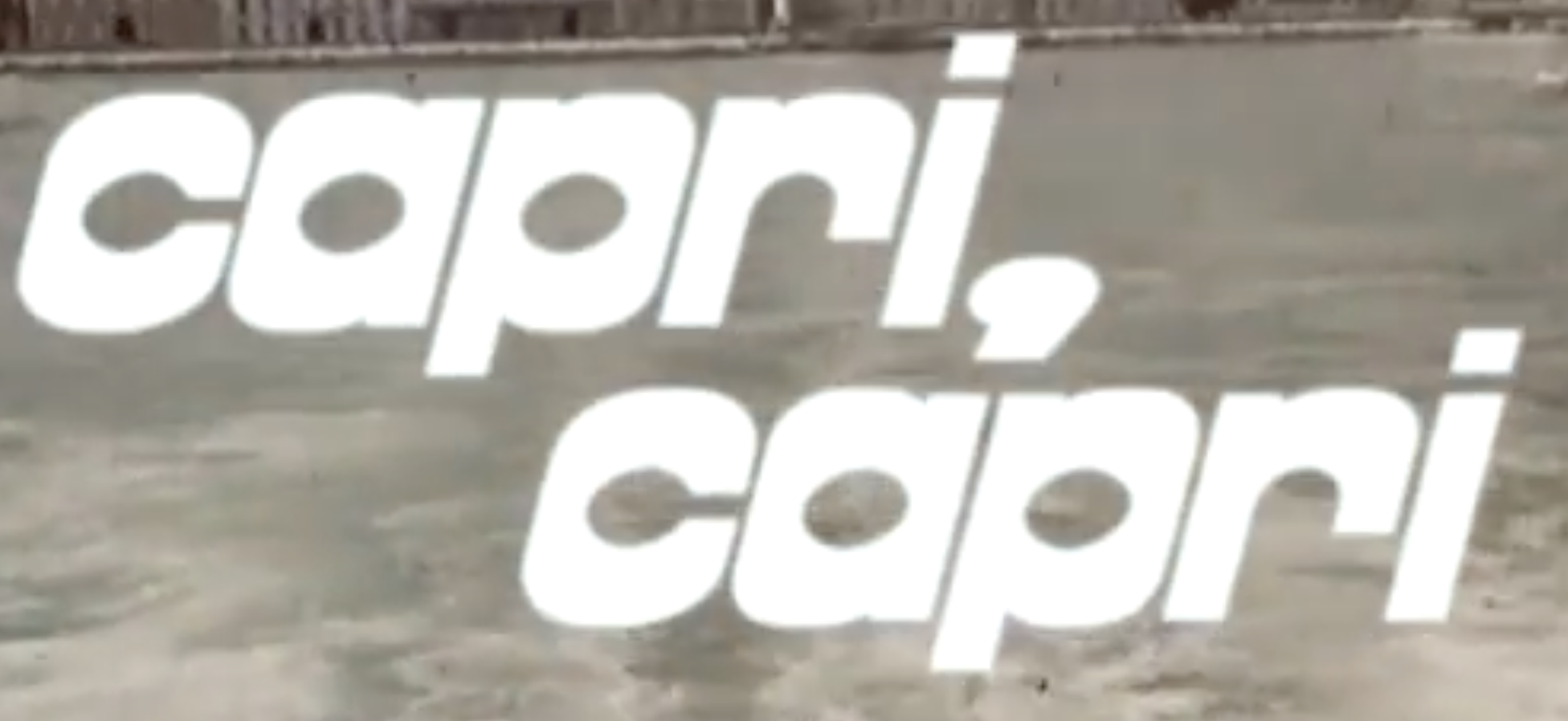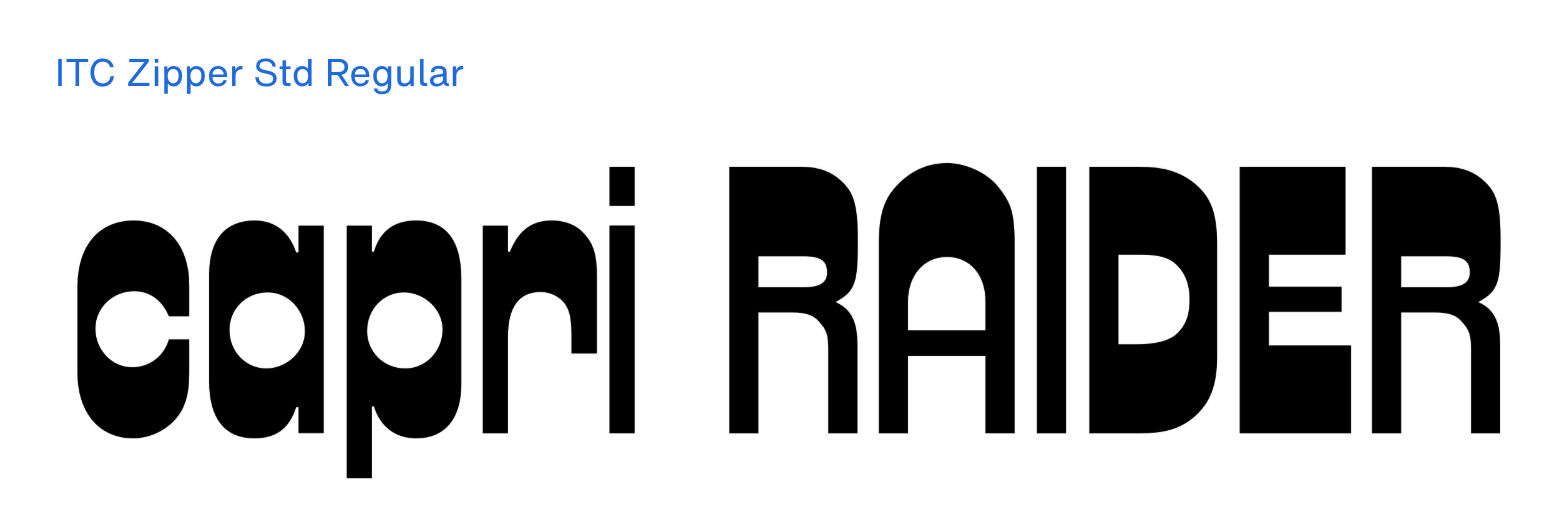
Filmtitel Capri, Capri
ich suche eine Schrift aus dem Vorspann eines italienischen Capri-Films beziehungsweise Reisefilms von 1966.
Die Schrift wird im gesamten Vorspann verwendet – sowohl in Versalien als auch in Kleinbuchstaben.
Sie ist sehr fett, breit und deutlich nach rechts geneigt. Besonders auffällig sind:
Kennt jemand den exakten Namen der Schrift oder eine historische Schriftprobe, in der sie vorkommt?
Da hat jemand die ITC Zipper verbogen …
Die Zipper erschien 1970, ist evtl. der Film ab 1970 und nicht schon 1966 erschienen? Oder wurde der Vorspann später erstellt?